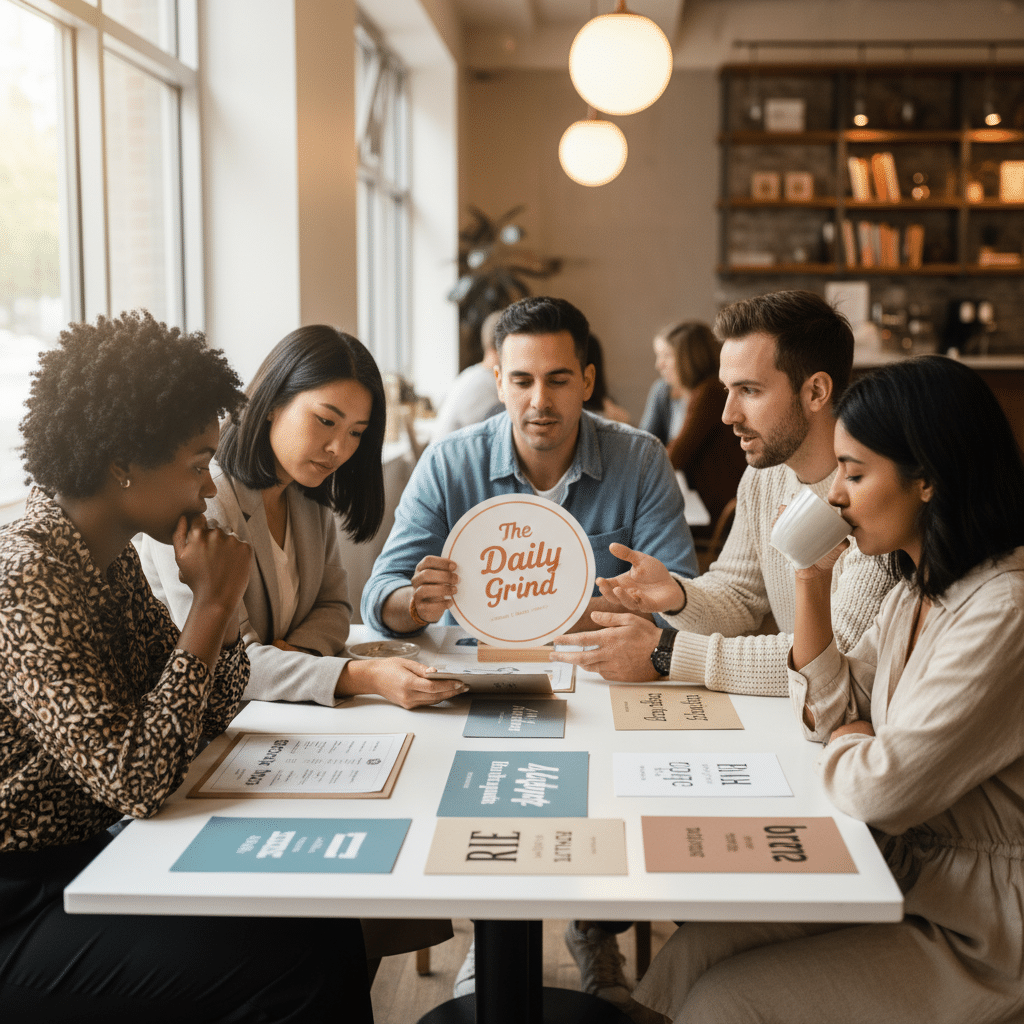
จิตวิทยาฟอนต์: เลือกฟอนต์โลโก้-เมนูยังไงให้ลูกค้าจำ
การเลือกรูปแบบตัวอักษร หรือ ฟอนต์ (Font) สำหรับโลโก้ เมนู หรือสื่อส่งเสริมการขายต่างๆ มีความสำคัญมากกว่าแค่ความสวยงาม แต่ยังส่งผลกระทบโดยตรงต่อการรับรู้ ความรู้สึก และการตัดสินใจของผู้บริโภค ศาสตร์ที่ศึกษาเกี่ยวกับเรื่องนี้เรียกว่า “จิตวิทยาฟอนต์” ซึ่งเป็นเครื่องมือสำคัญสำหรับผู้ประกอบการ SME ในการสร้างแบรนด์ให้เป็นที่จดจำและเข้าถึงกลุ่มเป้าหมายได้อย่างมีประสิทธิภาพ
สรุปประเด็นสำคัญเกี่ยวกับจิตวิทยาฟอนต์
- ฟอนต์สื่อสารบุคลิกภาพ: รูปแบบตัวอักษรแต่ละประเภทสามารถสื่อถึงอารมณ์และบุคลิกของแบรนด์ที่แตกต่างกัน ตั้งแต่ความน่าเชื่อถือ ความทันสมัย ไปจนถึงความเป็นกันเอง
- ความสอดคล้องคือหัวใจ: การใช้ฟอนต์ที่สอดคล้องกันในทุกช่องทางการสื่อสารช่วยสร้างภาพลักษณ์แบรนด์ที่แข็งแกร่งและเป็นที่จดจำได้ง่าย
- ความอ่านง่ายต้องมาก่อน: โดยเฉพาะในการออกแบบเมนูหรือสื่อที่มีข้อมูลจำนวนมาก ฟอนต์ที่อ่านง่ายจะช่วยให้ผู้บริโภครับสารได้อย่างรวดเร็วและไม่รู้สึกสับสน
- ความแตกต่างสร้างการจดจำ: การเลือกฟอนต์ที่มีเอกลักษณ์และเหมาะสมกับแบรนด์ จะช่วยให้ธุรกิจโดดเด่นเหนือคู่แข่งในตลาด
- ฟอนต์มีผลต่อการตัดสินใจซื้อ: การเลือกใช้ฟอนต์ที่กระตุ้นอารมณ์เชิงบวก เช่น ความสุข หรือความน่าเชื่อถือ สามารถโน้มน้าวการตัดสินใจซื้อของลูกค้าได้โดยไม่รู้ตัว
ทำความเข้าใจจิตวิทยาฟอนต์: พลังเงียบที่ขับเคลื่อนการตัดสินใจ
หัวข้อเรื่อง จิตวิทยาฟอนต์: เลือกฟอนต์โลโก้-เมนูยังไงให้ลูกค้าจำ เป็นศาสตร์ที่ศึกษาผลกระทบของไทโปกราฟี (Typography) หรือรูปแบบตัวอักษร ที่มีต่อความคิด อารมณ์ และพฤติกรรมของผู้รับสาร ในเชิงการตลาด ฟอนต์ทำหน้าที่เป็นเหมือน “ภาษากาย” ของแบรนด์ที่สื่อสารบุคลิกภาพและคุณค่าออกไปโดยไม่ต้องใช้คำพูด การเลือกฟอนต์ที่ถูกต้องจึงเป็นขั้นตอนสำคัญในการสร้างแบรนด์ที่แข็งแกร่ง เพราะมันสามารถสร้างความไว้วางใจ ดึงดูดกลุ่มเป้าหมายที่ใช่ และท้ายที่สุดคือการกระตุ้นยอดขาย
ความสำคัญของจิตวิทยาฟอนต์ทวีความสำคัญมากขึ้นในยุคดิจิทัลที่ผู้บริโภคถูกรายล้อมไปด้วยข้อมูลมหาศาล แบรนด์มีเวลาเพียงไม่กี่วินาทีในการสร้างความประทับใจแรก โลโก้บนป้ายร้าน เมนูอาหารในแอปพลิเคชันเดลิเวอรี่ หรือโพสต์บนโซเชียลมีเดีย ล้วนเป็นจุดสัมผัสแรกที่ฟอนต์เข้ามามีบทบาทในการกำหนดว่าลูกค้าจะมองแบรนด์นั้นอย่างไร ไม่ว่าจะเป็นธุรกิจร้านอาหาร คาเฟ่ สินค้าอุปโภคบริโภค หรือบริการต่างๆ การทำความเข้าใจในหลักการนี้จะช่วยให้ผู้ประกอบการสามารถเลือกเครื่องมือสื่อสารที่ทรงพลังนี้ได้อย่างมีกลยุทธ์ เพื่อสร้างความได้เปรียบในการแข่งขัน
ถอดรหัสอารมณ์ผ่าน 5 ประเภทฟอนต์ยอดนิยม
ฟอนต์สามารถแบ่งออกได้เป็นหลายประเภท แต่ละประเภทมีลักษณะทางกายภาพและจิตวิทยาที่สื่อสารออกมาแตกต่างกัน การทำความเข้าใจลักษณะเฉพาะของฟอนต์กลุ่มหลักจะช่วยให้การเลือกใช้งานเป็นไปอย่างแม่นยำและตรงตามวัตถุประสงค์ของแบรนด์มากขึ้น
ฟอนต์ Serif (มีเชิง): สัญลักษณ์แห่งความน่าเชื่อถือและความคลาสสิก
ฟอนต์ประเภท Serif มีลักษณะเด่นคือมี “เชิง” หรือ “เท้า” (Serif) อยู่ที่ปลายของเส้นตัวอักษร ซึ่งเป็นลักษณะที่สืบทอดมาจากการแกะสลักตัวอักษรบนหินในสมัยโบราณและพัฒนามาสู่การพิมพ์ในยุคแรกๆ ด้วยประวัติศาสตร์อันยาวนานนี้เอง ฟอนต์ Serif จึงมักถูกเชื่อมโยงกับความรู้สึกเป็นทางการ, ความมั่นคง, ความน่าเชื่อถือ, และความสง่างามแบบคลาสสิก แบรนด์ที่ต้องการสร้างภาพลักษณ์ที่ดูภูมิฐาน มีประวัติศาสตร์ยาวนาน หรือเน้นความเชี่ยวชาญ มักนิยมใช้ฟอนต์ประเภทนี้ เช่น สถาบันการเงิน, สำนักงานกฎหมาย, หรือแบรนด์สินค้าหรูหราอย่าง Cartier และ Coca-Cola ที่ใช้ฟอนต์ Serif เพื่อสื่อถึงความยิ่งใหญ่และคุณภาพที่เหนือกาลเวลา
ฟอนต์ Sans Serif (ไม่มีเชิง): ตัวแทนของความเรียบง่ายและทันสมัย
คำว่า “Sans” ในภาษาฝรั่งเศสแปลว่า “ปราศจาก” ดังนั้นฟอนต์ Sans Serif จึงหมายถึงฟอนต์ที่ไม่มีเชิงที่ปลายตัวอักษร ทำให้มีลักษณะที่ดูสะอาดตา เรียบง่าย และทันสมัย ฟอนต์ประเภทนี้ได้รับความนิยมอย่างสูงในยุคโมเดิร์นและในสื่อดิจิทัล เนื่องจากความชัดเจนและความสามารถในการอ่านได้ง่ายบนหน้าจอที่มีความละเอียดแตกต่างกัน จิตวิทยาที่ฟอนต์ Sans Serif สื่อออกไปคือความเป็นมิตร, เข้าถึงง่าย, ตรงไปตรงมา และมีความสดใหม่ จึงเหมาะสำหรับแบรนด์เทคโนโลยี, สตาร์ทอัพ, สินค้าแฟชั่น หรือธุรกิจที่ต้องการสื่อสารกับคนรุ่นใหม่ เช่น Red Bull และ Calvin Klein ที่ใช้ฟอนต์ประเภทนี้เพื่อสร้างภาพลักษณ์ที่ดูคล่องตัวและร่วมสมัย
ฟอนต์ Script (ลายมือ): สื่อสารความสร้างสรรค์และความเป็นกันเอง
ฟอนต์ Script หรือฟอนต์ลายมือ มีลักษณะเลียนแบบการเขียนด้วยมือ ทำให้เส้นสายมีความลื่นไหลและเป็นธรรมชาติ ฟอนต์ประเภทนี้สามารถสื่ออารมณ์ได้หลากหลาย ตั้งแต่ความหรูหรา โรแมนติก (ในฟอนต์ลายมือแบบตวัด) ไปจนถึงความสนุกสนาน ร่าเริง และไม่เป็นทางการ (ในฟอนต์ลายมือแบบน่ารัก) การใช้ฟอนต์ Script ช่วยสร้างความรู้สึกที่เป็นส่วนตัวและเข้าถึงได้ง่าย ทำให้ลูกค้ารู้สึกถึงความใส่ใจและความอบอุ่น จึงมักถูกนำไปใช้กับแบรนด์ที่เน้นความคิดสร้างสรรค์, สินค้าสำหรับเด็ก, ร้านอาหารที่ต้องการบรรยากาศเป็นกันเอง หรือการ์ดอวยพร ตัวอย่างเช่น โลโก้ของ Instagram หรือ Disney ที่ใช้ฟอนต์ Script เพื่อกระตุ้นความรู้สึกสนุกสนานและจินตนาการ
ฟอนต์ Modern: ภาพลักษณ์แห่งความหรูหราและแตกต่าง
ฟอนต์ประเภท Modern เป็นวิวัฒนาการต่อจากฟอนต์ Serif แบบดั้งเดิม โดยมีลักษณะเด่นคือความแตกต่างอย่างสุดขั้วระหว่างเส้นหนาและเส้นบาง และมีเชิงที่บางและเป็นเส้นตรง ทำให้ดูมีความโฉบเฉี่ยว, หรูหรา, และล้ำสมัย ฟอนต์ Modern มักถูกใช้เพื่อสร้างความรู้สึกที่โดดเด่นและมีสไตล์ เหมาะสำหรับแบรนด์แฟชั่น, นิตยสาร, หรือผลิตภัณฑ์ที่ต้องการวางตำแหน่งตัวเองในตลาดระดับบน การใช้ฟอนต์ประเภทนี้สามารถสื่อถึงความสดใหม่และความเป็นผู้นำในตลาดได้เป็นอย่างดี แบรนด์อย่าง Dunkin’ หรือ Mizuno เลือกใช้ฟอนต์ที่มีลักษณะทันสมัยเพื่อสะท้อนภาพลักษณ์ใหม่ของแบรนด์